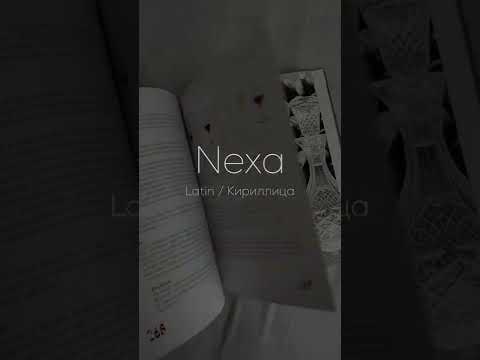
Качественные шрифты с поддержкой русского языка: как правильно выбрать
Не знаете, как выбрать шрифты, которые корректно отображают русский язык? В этой статье вы найдете полезные советы и идеи, которые помогут вам с выбором качественных шрифтов, подходящих для использования с русским языком.
При выборе шрифта обратите внимание на наличие кириллического набора символов. Убедитесь, что шрифт поддерживает нужные символы и знаки, используемые в русском языке, такие как буквы, знаки препинания и диакритические знаки.
Оцените читаемость и эстетическое впечатление, которое создает шрифт. Проверьте, насколько хорошо различимы его символы и насколько удобно читать текст, написанный данным шрифтом.
Потестируйте выбранные шрифты в различных условиях использования, например, на экране компьютера, мобильного устройства или в печати. Убедитесь, что шрифт выглядит хорошо и четко, и не вызывает трудностей при чтении на различных устройствах и в различных размерах.